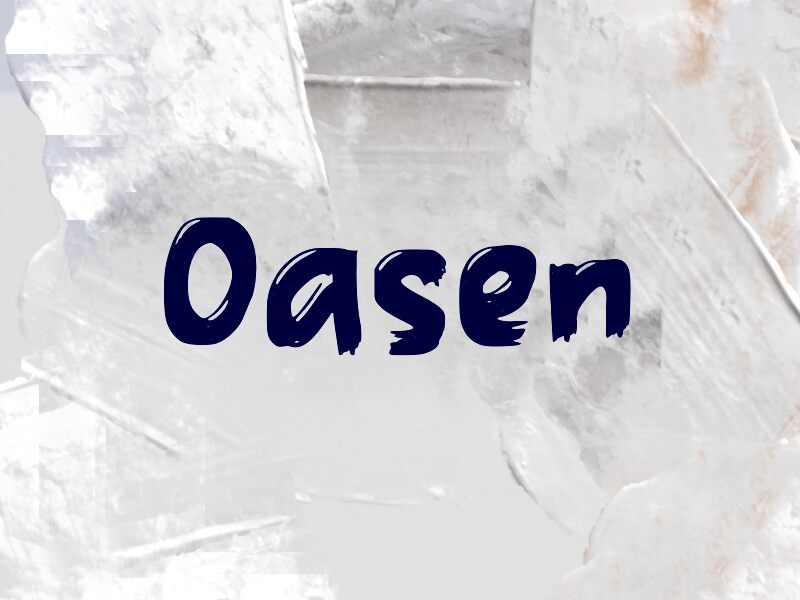
Oasen od Wep to darmowy krój pisma typu display w stylu «dry-brush» (suchy pędzel), z odważnym, malarskim rozmachem i surowym, skandynawskim charakterem plakatowym. Litery wyglądają jak nakładane i przeciągane, a nie starannie kreślone – mają grube łuki, ścięte krawędzie i nierówności, które nadają im luźny, nieco „nadgryziony” rytm.
Idealnie pasuje do brandingu kawiarni, etykiet na butelkach, plakatów eventowych, okładek płyt, książek czy krótkich nagłówków w mediach społecznościowych, gdzie potrzeba wyrazistego, malarskiego głosu, a nie wygładzonej kaligrafii. Użyj go do kart tytułowych, nazw na opakowaniach lub dużych nagłówków – szeroka faktura pędzla nadaje nawet krótkim słowom surowy, ręcznie wykonany charakter.